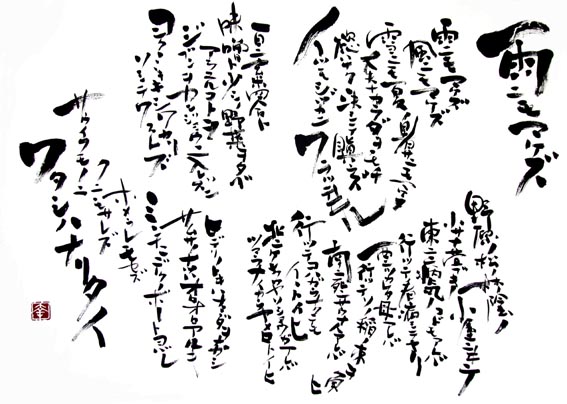
【書 「雨ニモマケズ(全文)」】 紙の大きさ:縦55cm×横75cm 仕上げ:裏打ちのみ (愛媛県:M.I様) |
雨ニモマケズ、人気ですね。みなさんが好きなのもわかります。読む程にジンとくるものがありますね。今回のご依頼はサイズが大きいこともあり、遊んだ配置で書く事ができました。新居のモダンな和室に合うようにとのご依頼だったので、お部屋の写真を送って頂き、それもふまえて書きました。そのため他にはないイメージのモダンな「雨ニモマケズ」になりました。